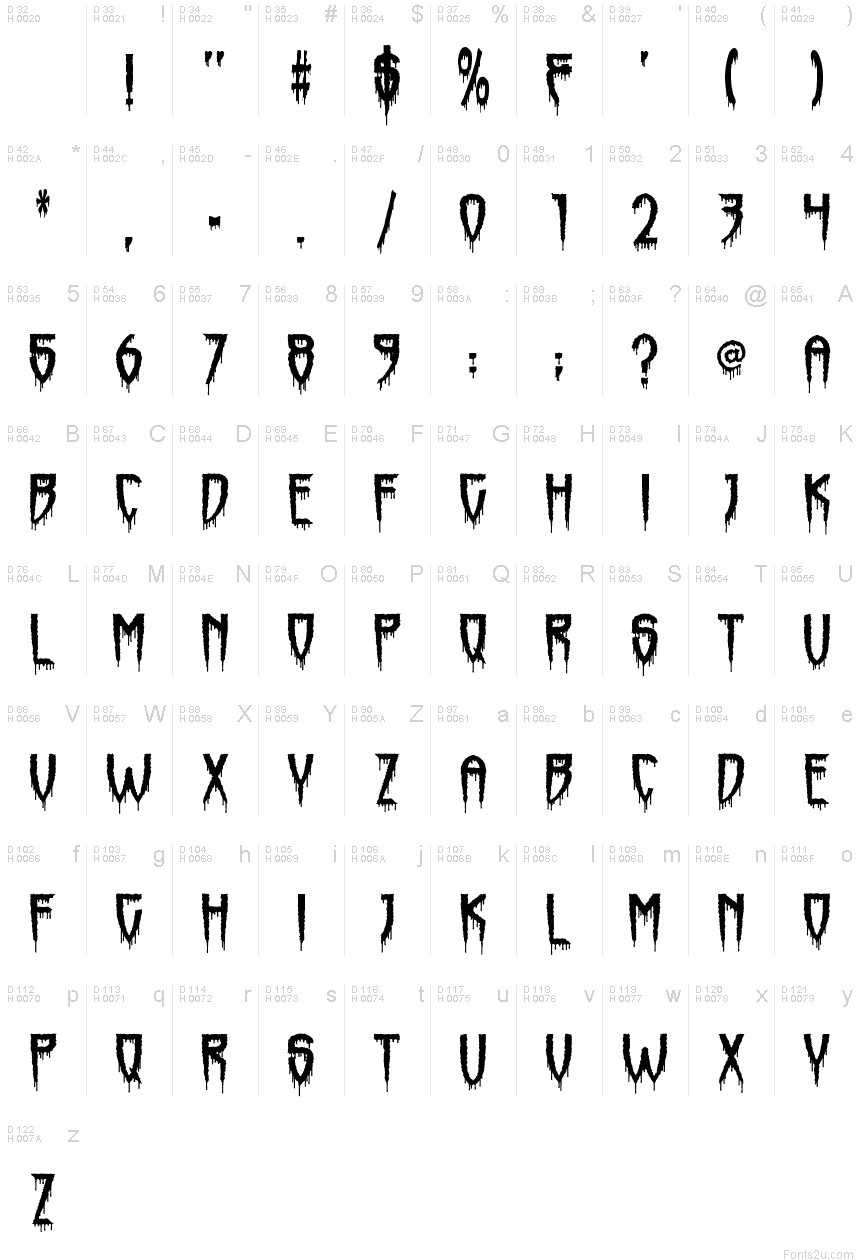
Horrorfind di Horrorfind.com è un carattere display gratuito dallo stile horror, che sembra inciso su un muro e lasciato a sanguinare. Le lettere, alte e appuntite, sfumano in lunghe gocce con bordi ruvidi e crostosi, che danno una sensazione di umido e inchiostrato. La texture è densa e caotica: ogni parola colpisce come un titolo urlato, ben lontano da un sobrio testo di lettura.
Questo font gratuito è perfetto per locandine di film horror, volantini di case infestate, inviti per feste di Halloween, branding di escape room, titoli di giochi e inquietanti miniature di YouTube. Usare Horrorfind in grandi dimensioni fa risaltare al massimo i dettagli gocciolanti; abbinalo a un carattere sans serif pulito e stretto per mantenere il tuo layout leggibile e carico di tensione.